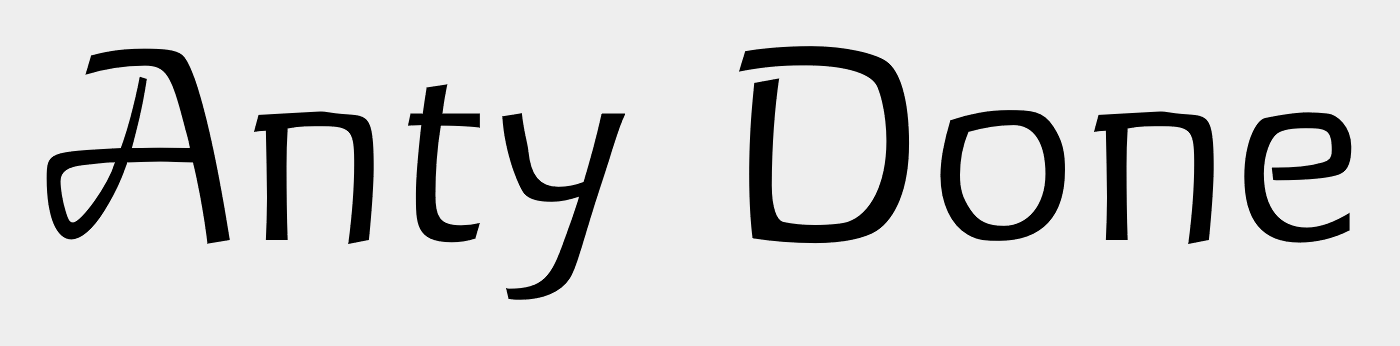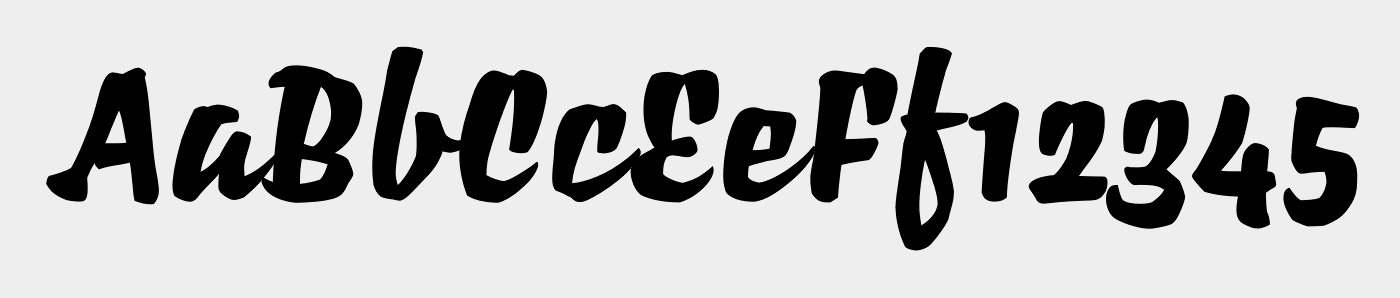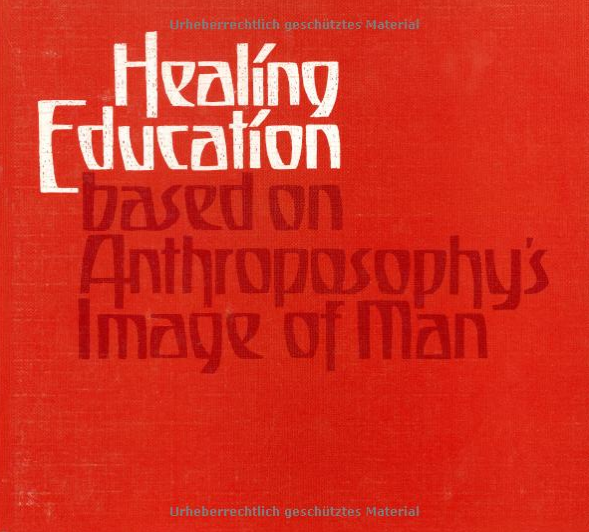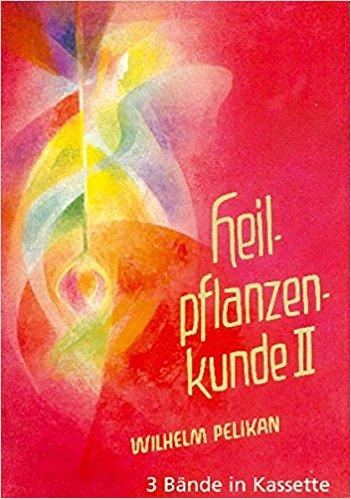
Anthroposophische Schriften
Wir hatten vor Jahren hier mal ein Thema in denen "Waldorfschriften" aufgezählt wurden, die bekanntesten sind ja von Lutz Baar (von ihm gibts auch noch andere) die RO-Schriften sowie der Waldorf Font von Joachim Frank. Leider finde ich den Thread nicht mehr.
Mir gefallen diese hölzernen, humanistischen Schiftformen eigentlich recht gut und da ich gerade ein Logo gestalten soll, welches diese Gestaltungsformen aufgreifen soll/darf bin ich gerade auf der Suche nach passenden Fonts. Diese ausgelutschte Waldorfschrift möchte ich eigentlich nicht verwenden, darum suche ich etwas alternatives. Vielleicht können wir mal ein paar Schriften mit diesem typischen Formen zusammensuchen, ohne die Ideologie dahinter zu beleuchten. Das dürfen auch gern alte Bleischriften sein, von denen es noch keine Digitalisierung gibt.
Hier mal ein paar Beispiele
Ich würde auch soweit gehen und Neuland von Rudolf Koch oder die Mendelssohn-Type hier mit aufzählen, also schon Richtung Linolschnitt. Auch die Antithesis und FF Amman von Yanone haben Züge dieser Formsprache.
Ich finde derartige Schriften sehen nur in ordentlich Fett gut aus ...
Gibt es denn schon eine Gestaltung(sidee)?
Schrift darf man sich nicht einfach so angucken, es muss auch immer auf das drumherum geguckt werden. Wenn man sich nur Schriften anguckt, wird man an jeder etwas auszusetzen haben. Vor allem einzelne Buchstabenformen sollten kein Ausschlusskriterium sein, weil man den Buchstaben ja nie einzeln betrachtet und die vermeintlichen Macken verschwinden vielleicht im Text ...
Danke schonmal für die Tipps, ich recherchiere auch gerade etwas und suche nach der Quelle der typischen Anthro-Schriften. Walter Roggenkamp (Ro-Schriften) hat ja viel in dieser Richtung gestaltet und ebenfalls wie Ingrid Liche, der Designerin der FF Liant für Weleda gearbeitet. Es gibt auch tolle Schriften auf Buchcovern von Ihm.
find ich persönlich sehr strange, weil sie weder fisch, fleisch noch stöckchen ist. von dem designer gibt es auch noch die Othello und Origami. Letzte ist an die arbeiten von Oldrich Menhart angelehnt, diese (und auch andere schriftentwürfe von Menhart) passt eigentlich auch gut in die liste. und wenn wir gerade bei Menhart sind:
Auch einen Blick wert:
Ich finde derartige Schriften sehen nur in ordentlich Fett gut aus ...
find ich persönlich sehr strange, weil sie weder fisch, fleisch noch stöckchen ist.
Mir gefallen die auch nicht alle. Aber darum ging doch erstmal nicht:
Vielleicht können wir mal ein paar Schriften mit diesem typischen Formen zusammensuchen,
Linolschnitt
schon richtig, hat ja auch keiner etwas gegen das zusammensuchen gesagt – war nur meine subjektive meinung zum font. wobei ich mir die eigentlich recht gut für den bereich pharmazie vorstellen kann.
auf alle Fälle ertappe ich mich immer wieder, dass ich ein Produkt in das Regal zurück stelle, sehe ich die typische Schrift.
Und gerade im Bereich Pharma erwarte ich da eigentlich bur hochgelobte Placebos.
auf alle Fälle ertappe ich mich immer wieder, dass ich ein Produkt in das Regal zurück stelle, sehe ich die typische Schrift.
Daher auch ein paar Vorschläge, welche etwas von dieser Richtung (FF Lian) abweichen. ;-)
Und gerade im Bereich Pharma erwarte ich da eigentlich bur hochgelobte Placebos.
Ich hab ja schon Lust, eine Homöopathie-Diskussion anzuzetteln. Bei sowas mach ich ja keine Gefangenen. :-D Aber ich beschränke mich mal darauf festzustellen, dass meine Weleda-Arnika-Salbe zu 30% aus Arnika besteht. Mit anderen Worten: Arnika ist in der Salbe chemisch nachweisbar. Und da Arnika nachweislich, u. z. nach wissenschaftlichen Kriterien, eine heilende Wirkung hat, darfst du von der Salbe mehr erwarten als den Placebo-Effekt.
Für ein "Anthropologo" im 21. Jh. würde ich etwas weiter weg von den Unzialformen gehen ... Hast du schon mal versucht, selbst etwas zu zeichnen? So nach dem Basisprinzip: keine senkrechten bzw. parallelen Linien und außen eckig/innen rund? Oder sind's schlicht zu viele Buchstaben?
Ich bin da ganz bei Dir! Die ersten Entwürfe wurden alle ohne den typischen Waldorfschriften abgegeben. Momentan ist die Anthesis mein Favorit. Selberzeichnen kann ich a) nicht, b) ist der Name dafür zulang und c) ist das Budget begrenzt. Ich will auch keine der typischen Waldorfschriften verwenden und will nur gewappnet sein, falls der Kunde danach verlangt, was gut möglich ist.
Mir ging es auch eher darum ein paar Alternativen aufzuzählen, welche auch passen könnten und nicht nach FF Liant aussehen.
... ging ja aber erstmal um den Stil. Inspirationen sammeln usw. Einsetzen würde ich sowas auch nie.